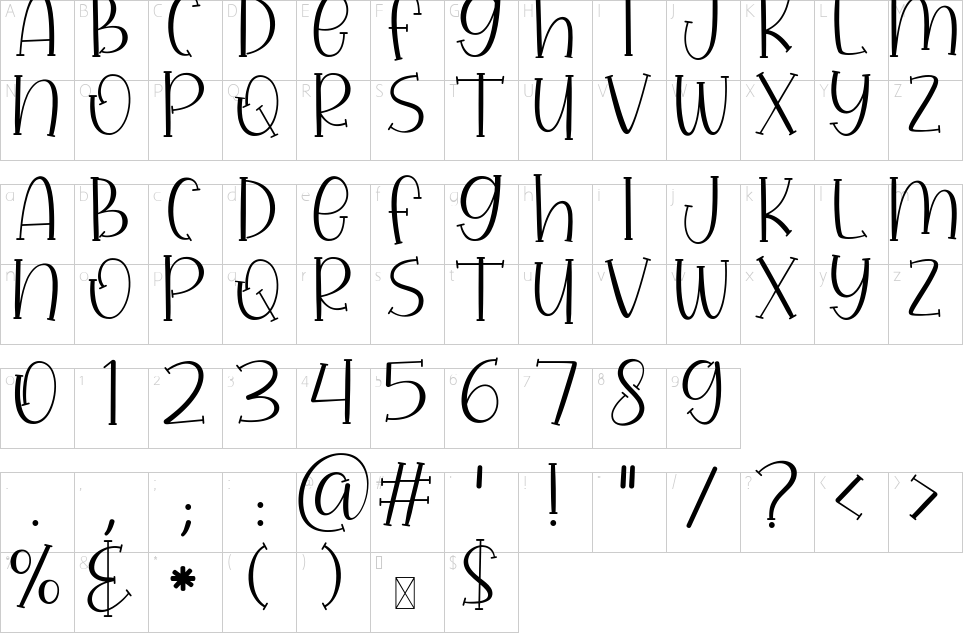
Descubra o charme e a elegância da fonte Amore Font, perfeita para personalizar seus documentos e layouts digitais. Desenvolvida pelo Studio Jimtype, essa fonte é uma delícia para os olhos, com linhas finas e espaçadas perfeitamente, que adiciona um toque romântico e sofisticado a qualquer design. Seja para criar cartões de convidado, projetos de design gráfico ou até mesmo para decorar seu site personalizado, a Amore Font é uma escolha ótima. Com 441 downloads, é uma opção popular e segura para quem busca uma fonte de qualidade sem pagar. Instale-a em seu sistema para desfrutar da sua elegância e versatilidade. Experimente hoje mesmo e descubra por si mesmo o que muitos usuários encontram incrivelmente atraente e funcional.